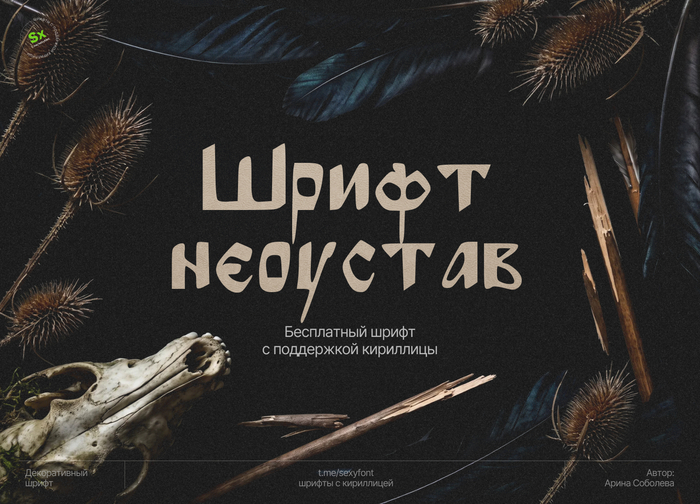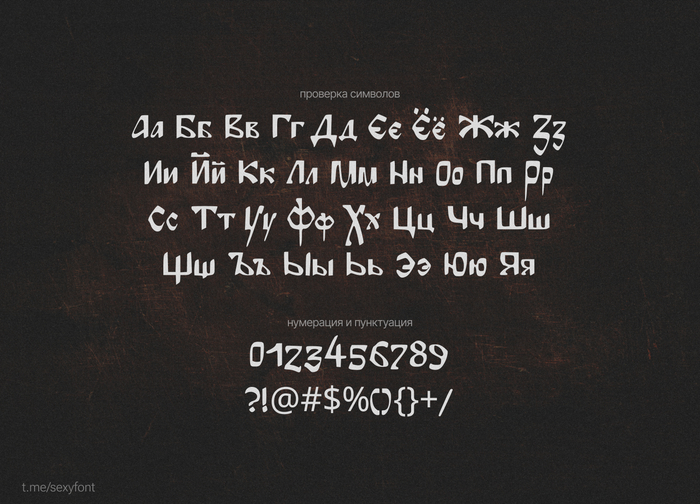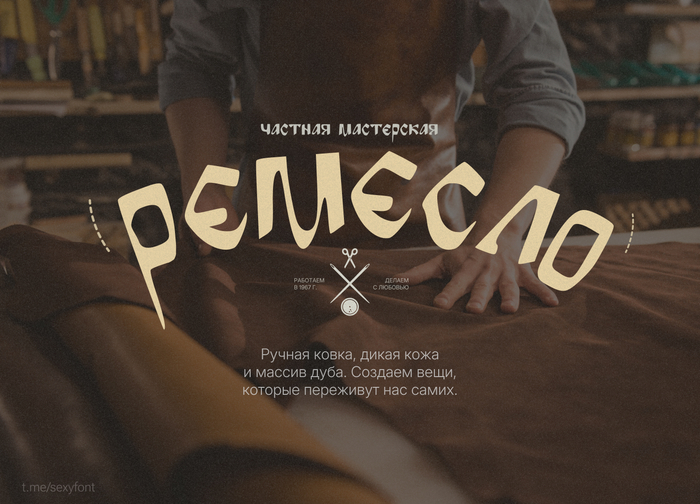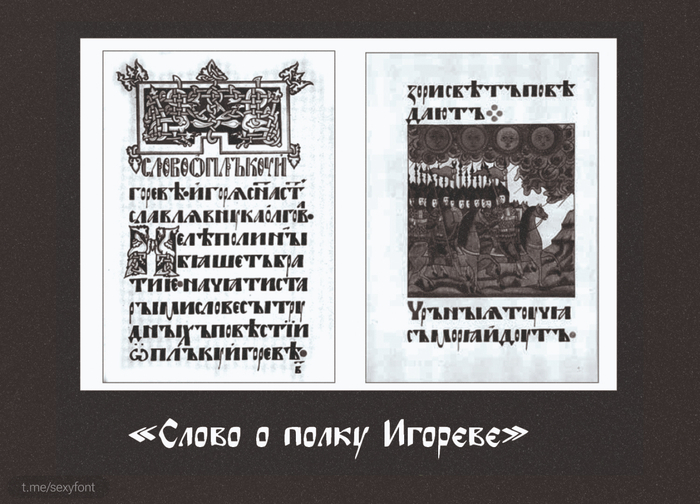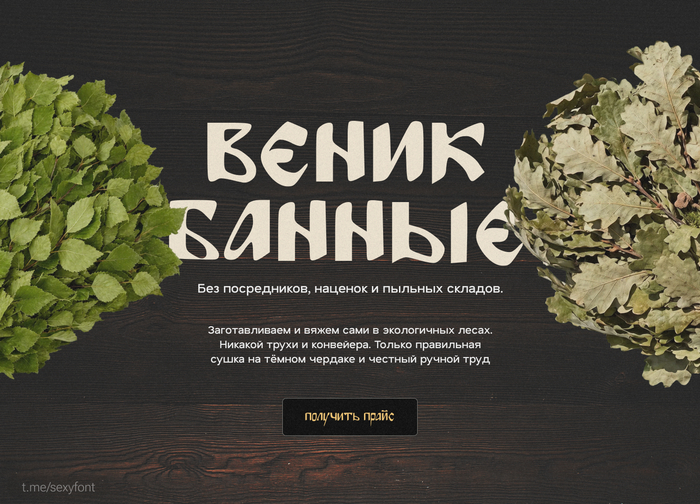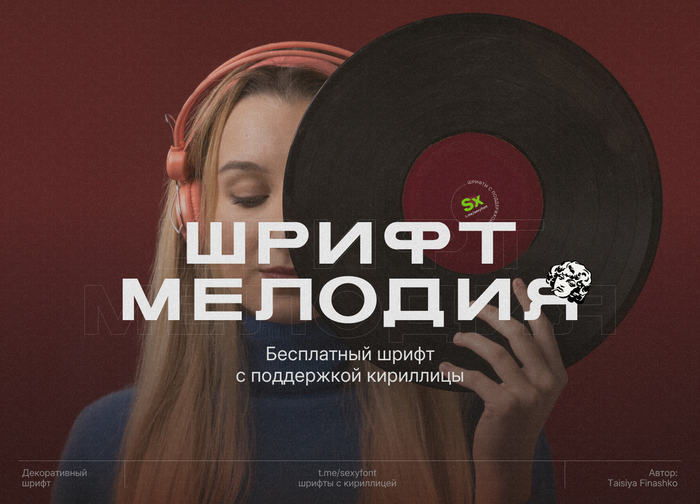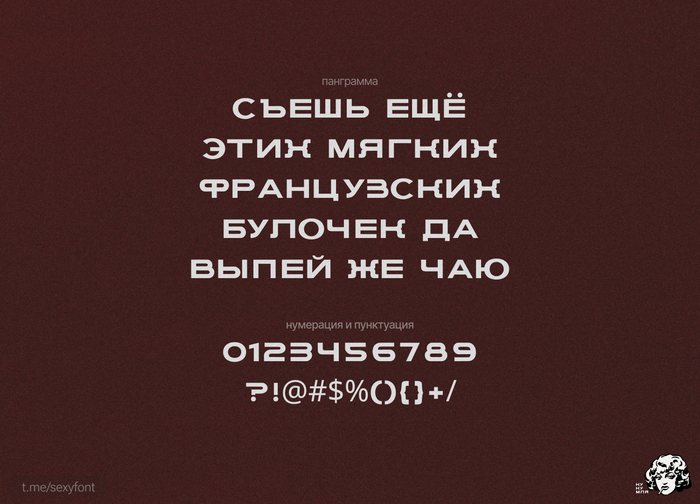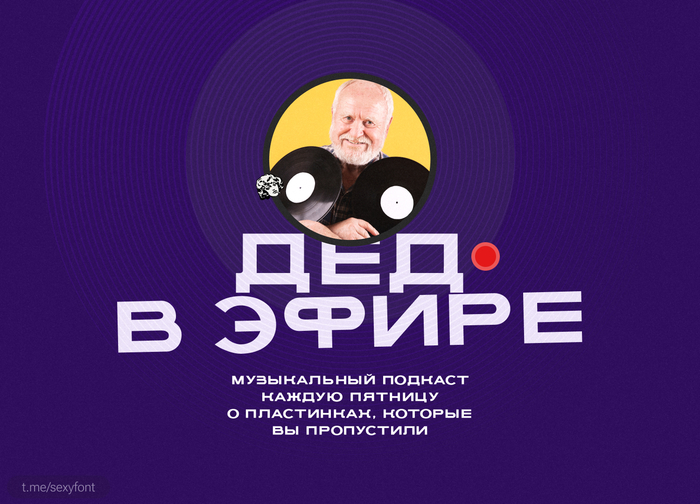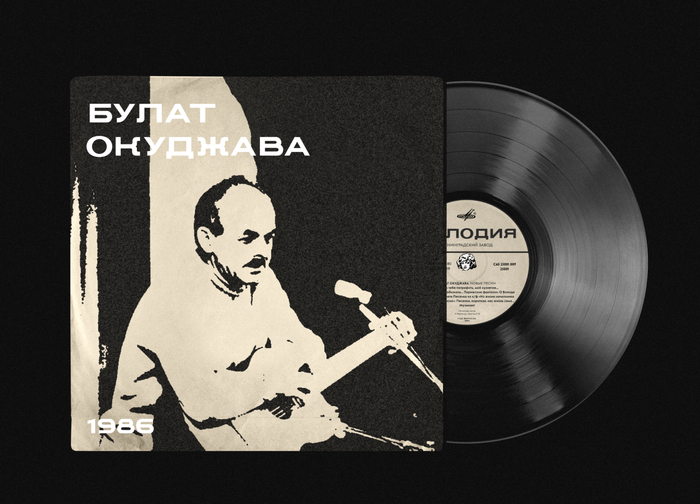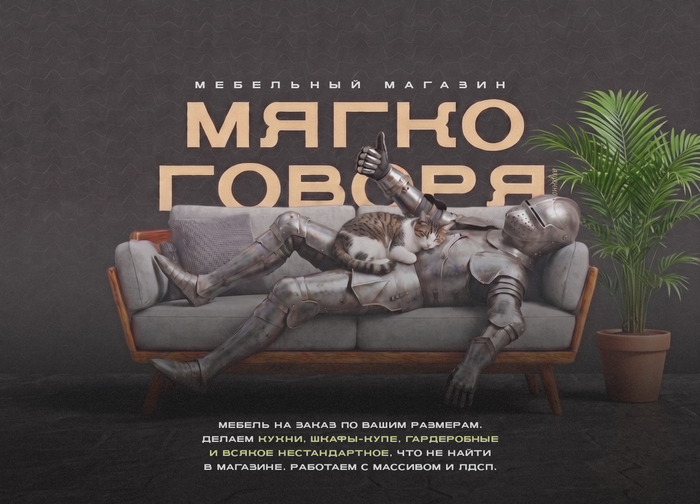
Бесплатный Шрифт Neoustav⁠⁠
Декоративный акцидентный шрифт на базе неорусской каллиграфии начала XX века. В основе — переосмысление стилизованного круглого устава писца Ивана Блинова (издание «Слова о полку Игореве» 1910 года).
Автор: Арина Соболева
Шрифт melodi⁠⁠
Привет. Лови еще один шрифт. Называется melodi. Жирный квадратный гротеск с лёгким ретро-душком. Плотный, тяжёлый, немного в духе старых вывесок.